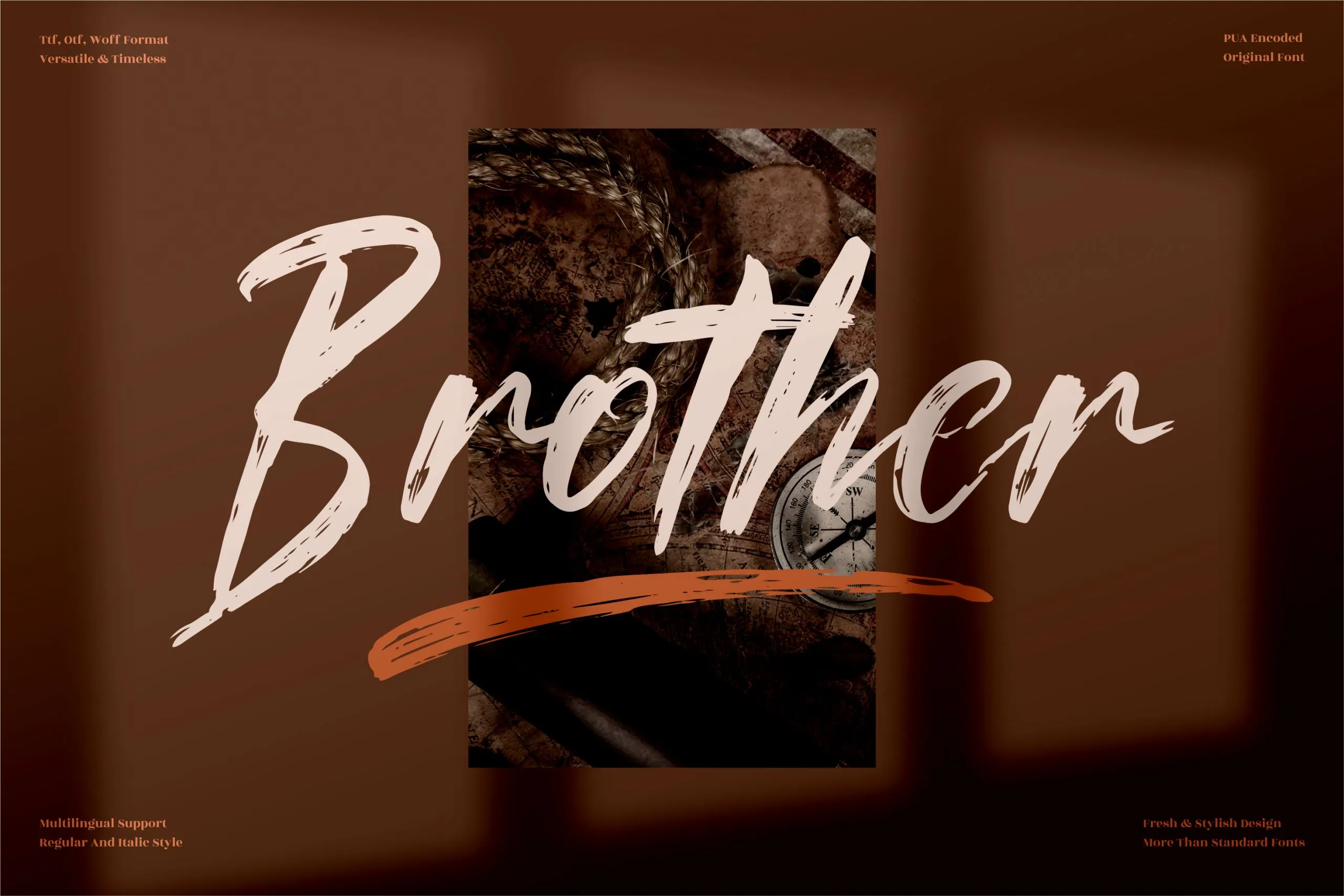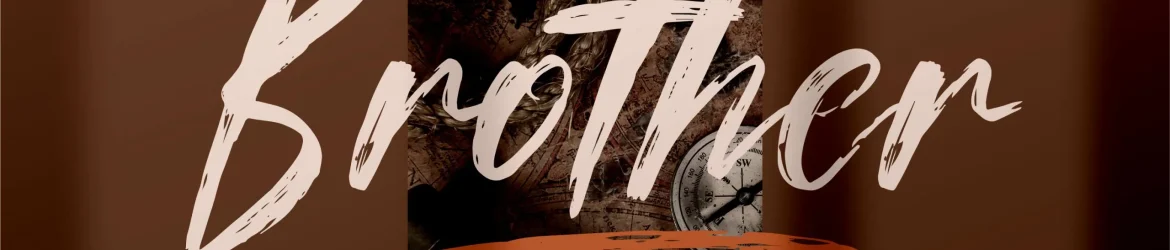
A fonte “Brother Font” é uma escolha perfeita para quem busca um toque único e autêntico em suas criações visuais. Seu estilo brush, criado pela perspectype, oferece uma sensação de mão humana que se adapta a uma ampla variedade de projetos. Essa fonte handwritten é ideal para qualquer aplicação, como logos, designs de branding, arte de móveis, embalagens de produtos, talheres e xícaras personalizados, marcos de citações, postais, cartões de visita, cartões de cumprimentos, etiquetas, fotos, impressões digitais, eventos especiais, além dos mais detalhados e requintados projetos pessoais. A fonte “Brother Font” é um complemento perfeito para designers que desejam dar vida aos seus projetos com um toque autêntico e delicado.